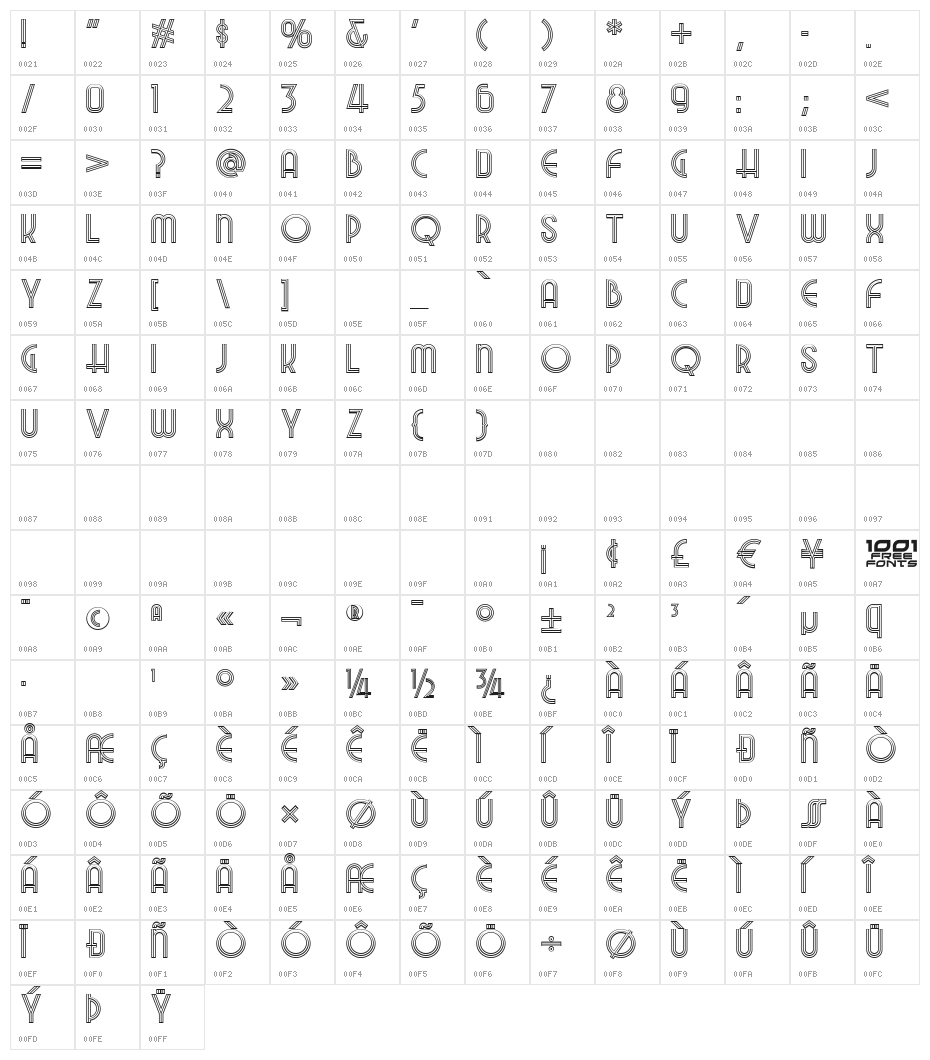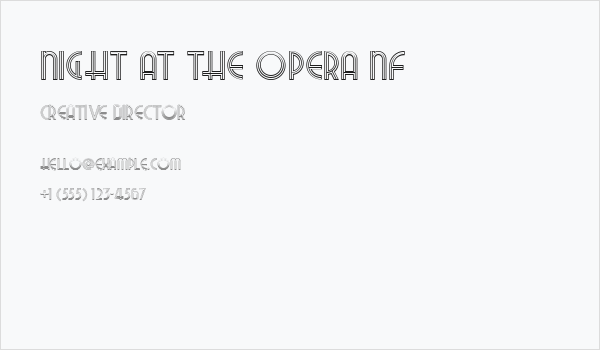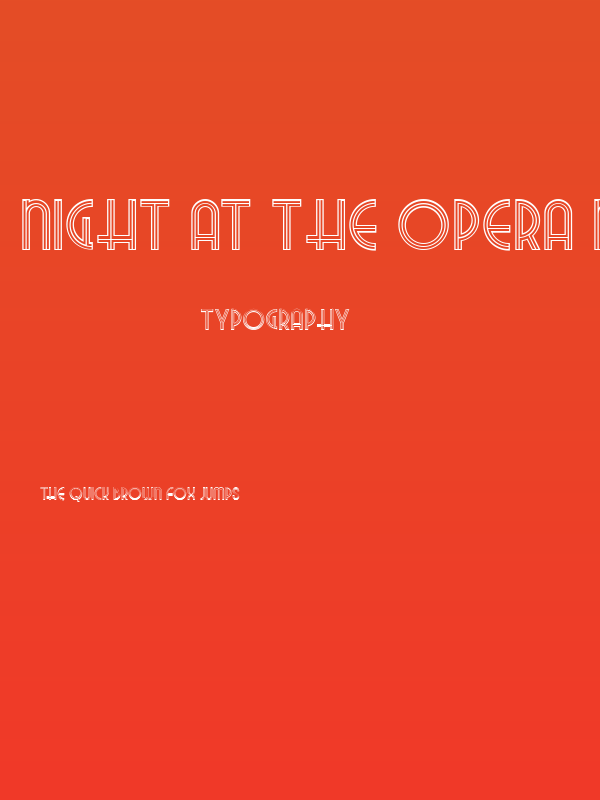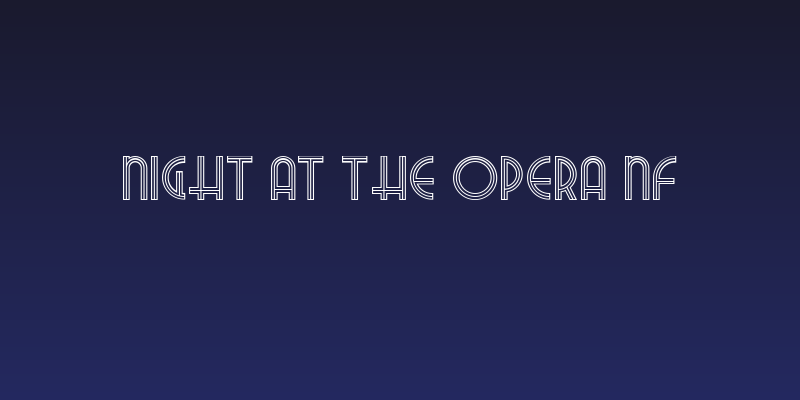
Night At The Opera NF Font
| Kategorien | Outline |
| Gesamtstil | Art Deco, Modern |
| Vorgeschlagene Projekte | Ideal for branding, posters, invitations, and any design needing a vintage yet modern aesthetic. |